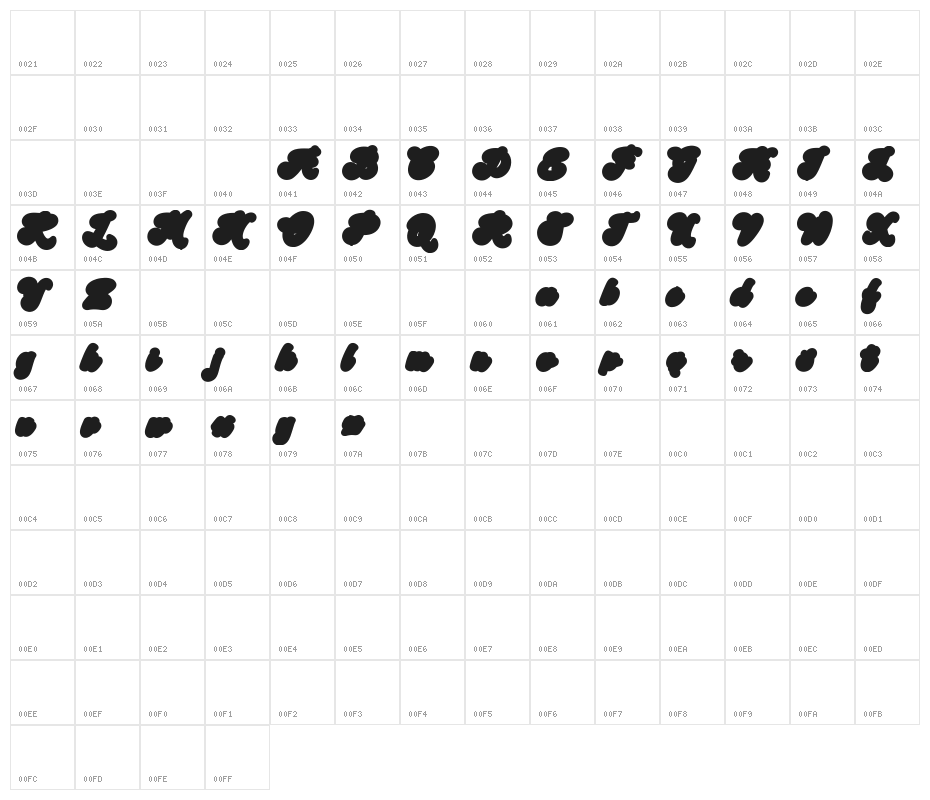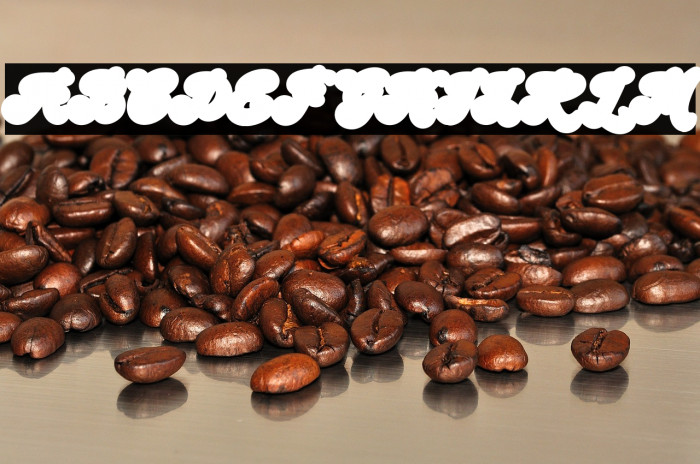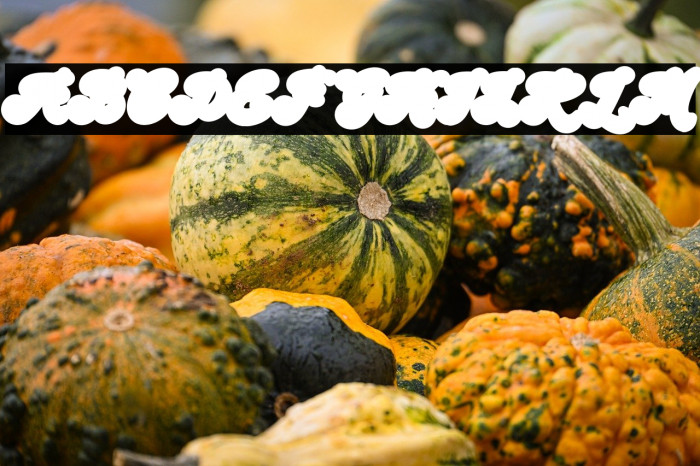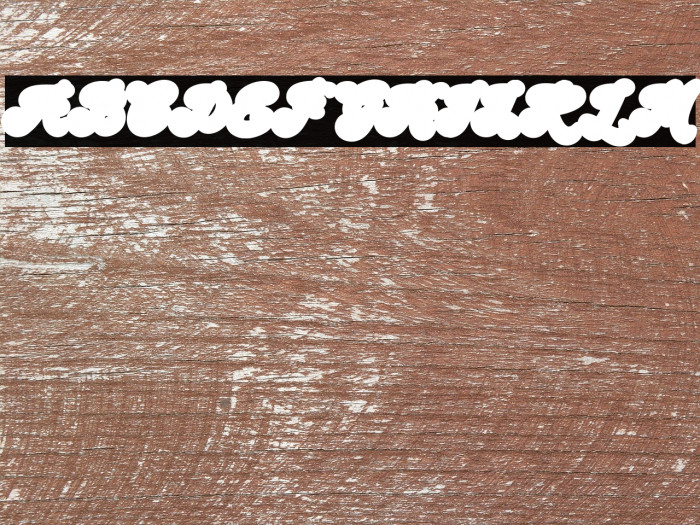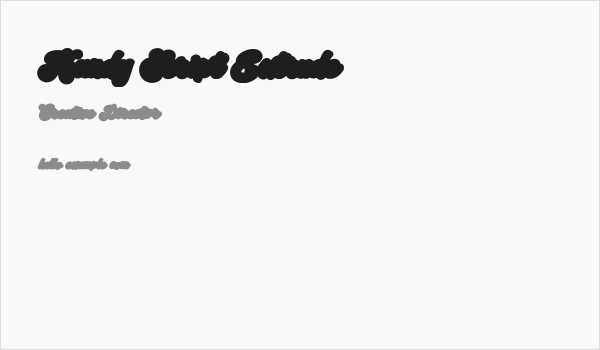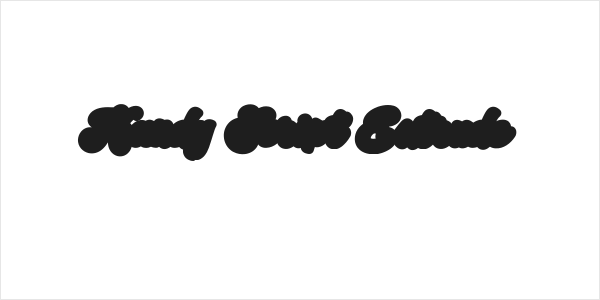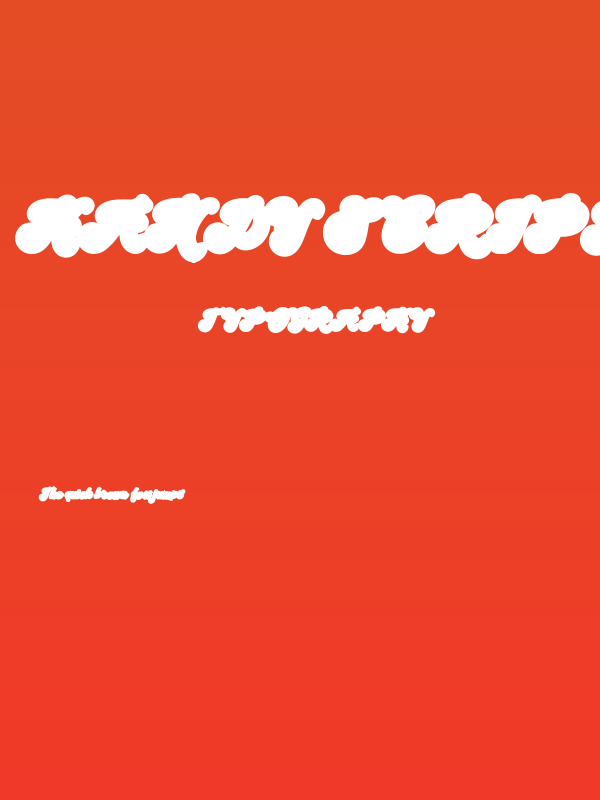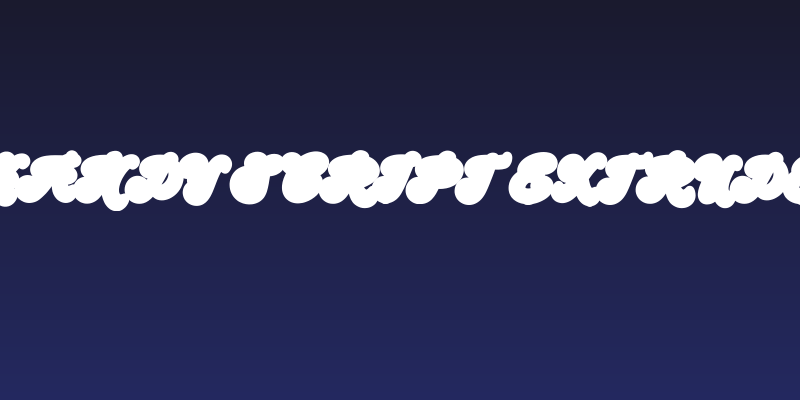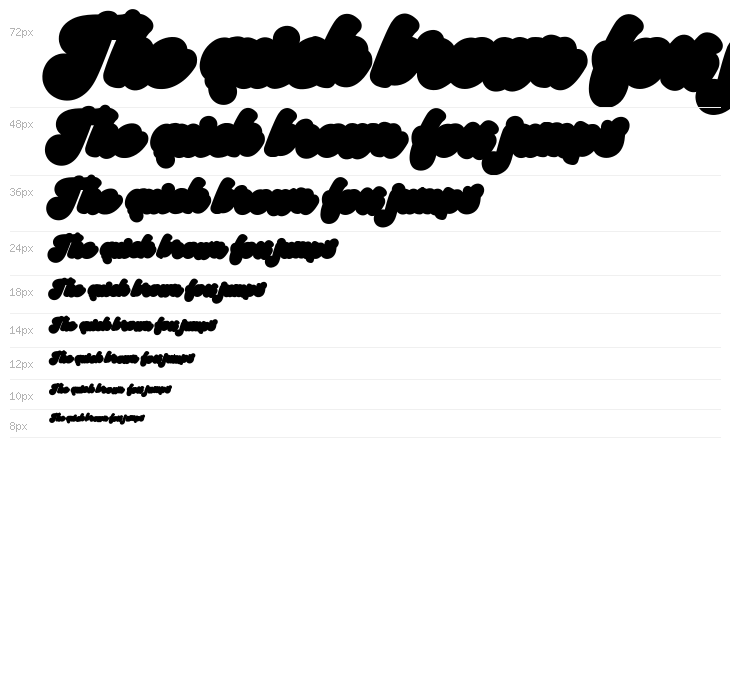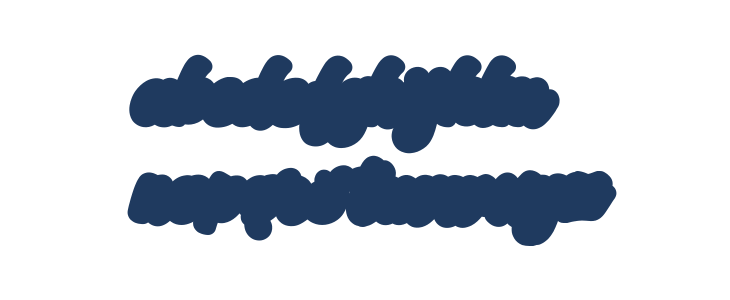
Handy Script Extrude Font
| Stile generale | Playful, Whimsical |
| Progetti proposti | Ideal for children's book covers, playful branding, party invitations, and creative posters. |